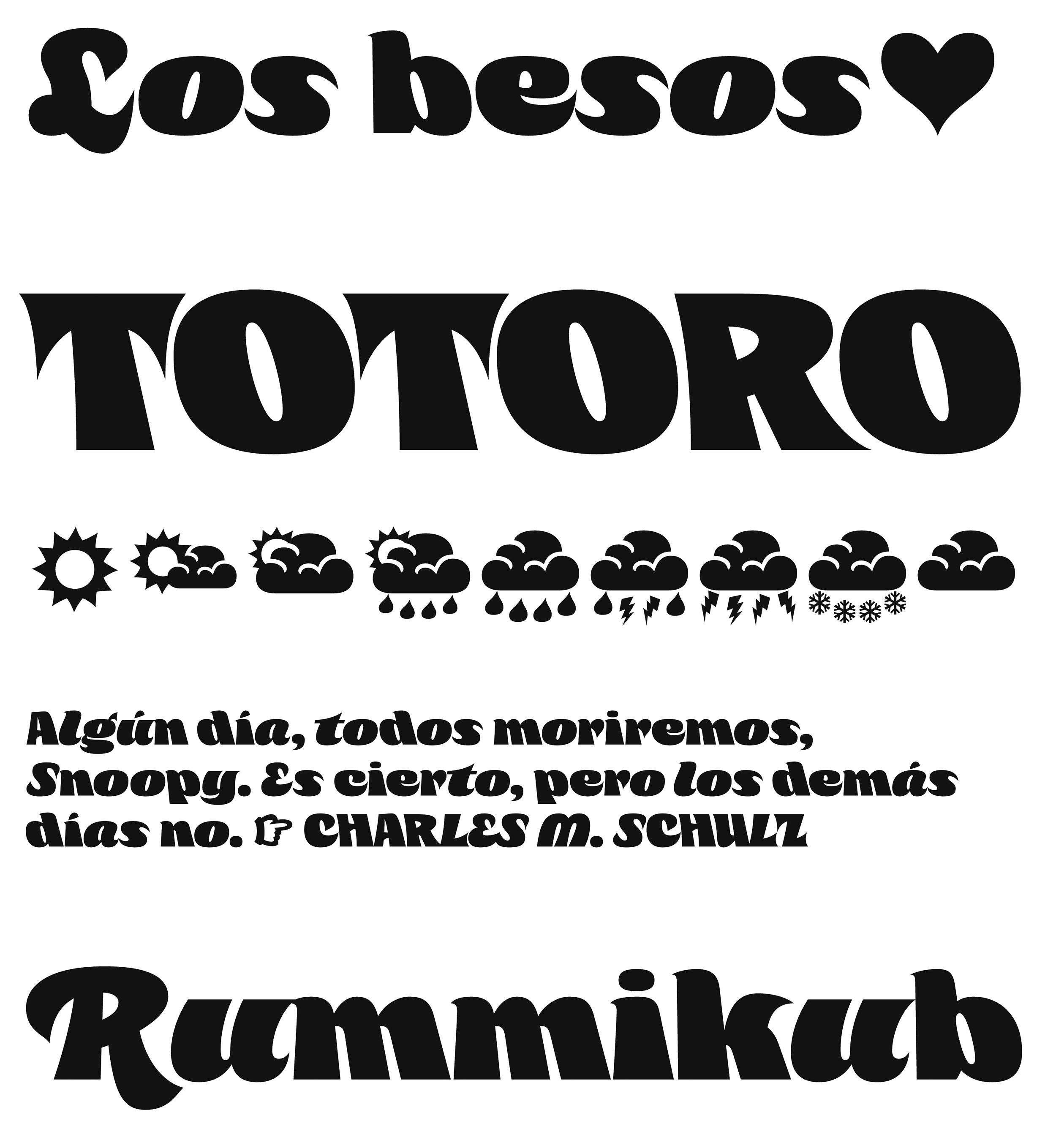
| Descripción | Simona es una tipografía tan audaz como el negro, diseñada para titulares desenfadados y destacados alegres, siempre en tamaños grandes y frases cortas. La idea principal de Simona es lograr una tipografía cursiva y cursiva inversa muy negra, que funcione en una sola fuente. Así, combinamos letras que van y vienen creando un ritmo vertiginoso que aporta un aire fresco a la tipografía de gran tamaño. |